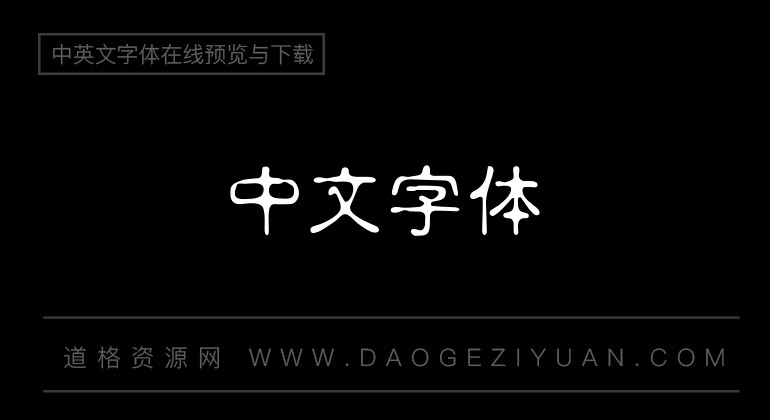
超世纪中古印体繁
超世纪中古印体繁是一款繁体中文字体,由超世纪字体设计工作室设计。该字体以中古印刷字体为基础,融合了新文艺复兴时期的精美风格,具有浓郁的古典气息,极具艺术感。字体以古典繁体汉字为主,并配有简体汉字,因此具有极强的汉字表达能力,适用于中文排版、中文印刷和中文排版。此外,该字体还具有良好的可读性和可视性,可以满足多种排版需求,为用户提供良好的排版体验。
超世纪中古印体繁是一款非常不错的手写艺术字体,具有很好的视觉感,适合于文化类的宣传设计、商业类品牌的广告和产品包装设计以及个性化文字排版等较多场景。
超世纪中古印体繁字符映射图